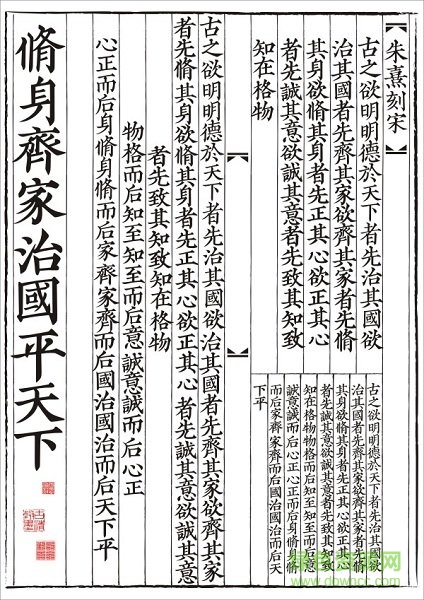
朱熹刻宋是彥辰設(shè)計推出的一款刻宋字體,還原宋刻本古籍字體特色,給人鐫刻印刷的視覺體驗(yàn),文字質(zhì)樸而大氣,結(jié)構(gòu)端正而松疏有致,十分簡潔好看,綠色資源網(wǎng)今日推薦!
“朱熹刻宋”字體設(shè)計以宋朝淳佑朱熹注解的《大學(xué)章句》刻本字形為藍(lán)本,將刻本字體按照現(xiàn)代平面設(shè)計需求進(jìn)行了修復(fù)、調(diào)整和優(yōu)化,設(shè)計師對大部分字形進(jìn)行了框架保留,將刀工失真之處進(jìn)行了機(jī)械性修復(fù),使其成為符合現(xiàn)代版式審美需求的新字形,同時盡量呈現(xiàn)宋刻本的原汁原味,整體感觀上更加古樸淵雅。
在古籍善本市場上,宋刻本無疑是皇冠上的鉆石。自明中后期以來,宋刻本一直受到學(xué)者、藏書家的特別重視。早在明朝,宋刻本已有“寸紙寸金”之說。
宋刻本之美主要在于字體、版式。事實(shí)上,中國自唐代就已有雕版印書,五代有以國子監(jiān)為代表的官刻本,但雕版印刷卻長期未被普遍采用,而仍以手抄的寫本為主,原因之一就是,寫本洋溢著書法藝術(shù)氣息,其美感使人油然產(chǎn)生閱讀的愉悅。而初始的雕版印刷品,常常會有滯澀呆板、索然無味的感覺。
中國的書法藝術(shù),歷經(jīng)漢代、南北朝及唐代三個高潮之后,到了宋代已極為繁榮。宋代為推廣雕版印刷,也從書法的角度考慮兼顧實(shí)用性和觀賞性。從目前留存的北宋版和南宋刻本的名品看,幾乎都出自擅長書法的人之手,且書體風(fēng)格不一,歐、虞、顏、柳、褚等爭奇斗妍,富于變化,加上雕印講究(紙墨精良,刻工也懂書法),藝術(shù)之美躍然紙上。